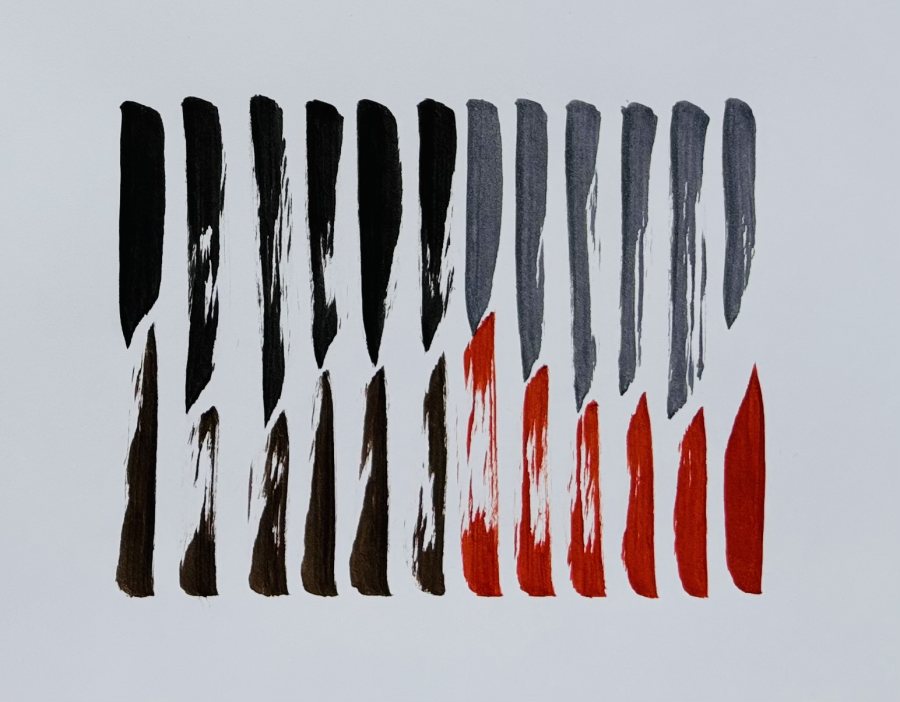
Pocket Brush Pen von Pentel im Test
Flexibel, vielseitig und für geübte Hände ein echtes Highlight
Der Pinselstift von Pentel, den ich zum Testen in den vier verfügbaren Farben Schwarz, Grau, Sanguine und Sepia erhielt, ist vergleichsweise leicht und liegt angenehm in der Hand. Jeder Stift ist äußerlich schwarz und hat in der Mitte einen kleinen Ring in der Farbe der mitgelieferten Tintenpatrone. Auch die Kappe hat ein abgerundetes Ende in dieser Farbe – so kann man die Stifte gut voneinander unterscheiden.
Handhabung und Tinte
Die Patrone lässt sich einfach und sauber ins Gehäuse drücken. Nach wenigen Minuten Wartezeit ist die pigmentierte Tinte bis ganz nach vorne in die etwa 1 cm lange weiße Spitze des Stiftes gelaufen.
Schon die ersten Schreibversuche zeigen die Eigenschaften des Pinselstiftes: Die Spitze ist weich und flexibel, Strichstärken von ungefähr 0,5 bis 5 mm sind möglich. Man spürt keinen Gegendruck, fast so, als würde man mit einem Rundhaarpinsel schreiben. Der Stift gleitet über das Papier und nimmt jede kleine Bewegung mit. Wie beim Malen sieht man sofort, ob man eine ruhige Hand hat und den Druck kontrollieren kann. Bei starker Druckausübung oder schnellen Strichen fransen die Ränder manchmal aus – für mich sind das aber reizvolle Effekte.
Die Tinte fließt stets gut nach. So kann man sogar in Gegenrichtung schreiben oder malen, etwa einen Kreis in einem Zug, ohne absetzen zu müssen.
Erste Versuche
Mein erstes Bild mit den Brush Pens: ein Frauenkopf, Kreise im Hintergrund, ein kleiner Blumenkasten und ein paar Wörter. Zuerst mit Bleistift vorgezeichnet, dann mit Schwarz und Sanguine nachgezogen, Bleistiftreste radiert und anschließend einige Elemente mit Aquarellfarbe übermalt. Dabei fiel mir auf: Die wasserfeste Tinte trocknet zwar innerhalb von Sekunden, man sollte aber sicherheitshalber prüfen, ob sie schon fest ist, um nichts zu verwischen. In meinem Fall haben die Aquarellfarben die Linien etwas verblassen lassen – ein schnelles Nachziehen mit dem Stift hat sie wieder kräftig gemacht.
Das Bild „Creating letters“ zeigt alle vier Farben: „Creating“ in Schwarz und Grau, „letters“ in den beiden Brauntönen.
Beim Bild „Die Welt im Wandel“ habe ich die Brauntöne (Sanguine und Sepia) zusammen mit einem schwarzen 0,1 mm Fineliner verwendet.
Auf Transparentpapier
Auch auf Transparentpapier funktioniert der Pocket Brush gut. Ich habe mit dem grauen Stift gearbeitet und das beschriebene Transparentpapier im Garten vor Pflanzen und Gräser gehalten. Fotografiert ergeben sich tolle Effekte: die Kalligrafie im Vordergrund, dahinter das Spiel von Licht und Schatten.
Mein Fazit
Ich würde den Pocket Brush Pen allen empfehlen, die gerne Handlettering machen und darin schon etwas geübter sind. Mit seiner weichen Spitze verlangt er eine ruhige Hand, wenn das Schriftbild gleichmäßig werden soll. Feine Linien verwackeln schnell, daher sind Fineliner oder härtere Brush Pens für Anfänger wahrscheinlich einfacher.
Die vier Farben lassen sich schön kombinieren, nur das Grau könnte für meinen Geschmack heller sein, da es sich kaum vom Schwarz abhebt. Überlagert man Linien, wird das Grau noch dunkler und unterscheidet sich kaum.
Geeignet ist der Pocket Brush Pen zum Schreiben, Zeichnen, für Mangas oder Comics. Dank der flexiblen Pinselspitze entstehen spannende Effekte, die sich mit Aquarellfarben, Markern, Bunt- oder Filzstiften weiterbearbeiten lassen.
Nach zwei Wochen intensiver Nutzung zeigt sich kein Verschleiß: Die Spitze ist formstabil, franst nicht aus und haart nicht. Die Patronen sind ergiebig und die Stifte trocknen selbst bei Temperaturen um 25 bis 30 Grad nicht ein.